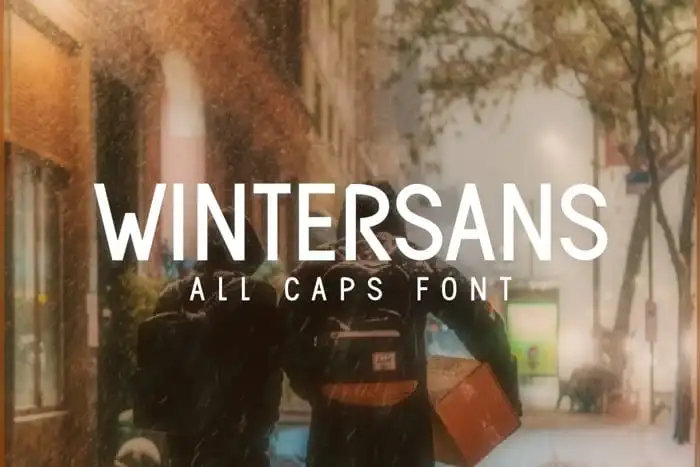
Wintersans Sans Serif Font – Fonte Grátis
Wintersans Sans Serif Font
Wintersans Sans Serif é uma fonte inspirada na rua Carnaby Street de Londres, repleta de personalidade e sofisticação. Essa elegante sans serif é produzida pela marca de fontes de qualidade de deedeetype. Seja ela usada em fundos agitados ou como um título de destaque sozinho, Wintersans sempre se sai bem, trazendo uma aparência impecável e atemporal a qualquer projeto gráfico. É perfeitamente adaptável para qualquer situação, seja ela formal ou informal, garantindo que sua mensagem seja reconhecida e impactante. Descubra por si só como essa fonte pode revolucionar suas criações visuais.